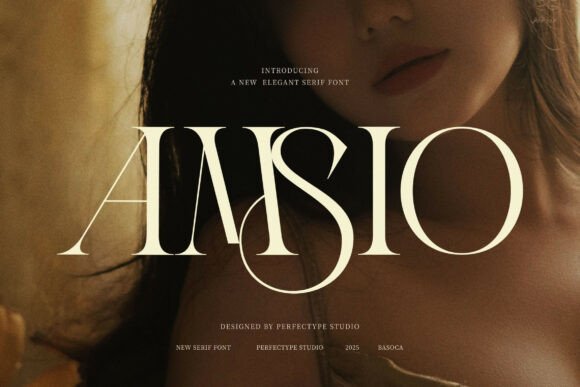
Amsio Elegant Serif
Amsio Elegant Serifのような高品質の素材をお探しの場合、このプレミアムパッケージはクリエイティブなプロジェクトに素晴らしい選択です。
精密に作られたAmsio Elegant Serifは、クリーンなベクター、滑らかなタイポグラフィ、そして安心のための商用ライセンスを提供します。
POD(オンデマンド印刷)製品、結婚式の招待状、またはソーシャルメディアのグラフィックを作成している場合でも、Amsio Elegant Serifは理想的です。